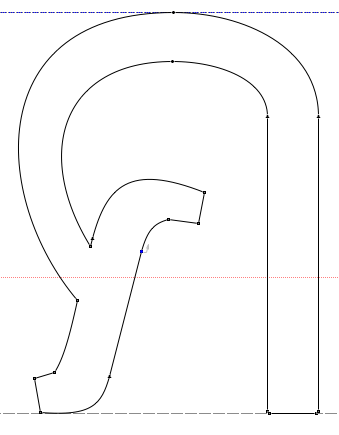
Opentype / Truetype
พอดีช่วงนี้ผมเริ่มอยากลงลึกศึกษาในตัวโปรแกรมมากกว่าศึกษาดีไซน์ครับ
แต่บ้านเรานี่หาอะไรพวกนี้อ่านยากเหลือเกิน ต้องรอผู้รู้  :56:
:07:  แต่จริงครับ ที่ตำราแนวนี้หาอ่านยากครับ อย่าว่าแต่ภาษาบ้านเรา ภาษาปะกิตก็ยังหาอ่านยากอยู่ แม้จะพอหาได้บ้างก็ตาม เป็นศาสตร์ของชนกลุ่มน้อยครับ
:25:  อ้อ...จะบอกว่า อีกข้อนึงคือ ถ้าเราวาดเวคเตอร์ตัวต้นฉบับไว้ได้แบบกิ๊ง กิ๊ง จุดแบบทรูไทป์ก็จะน้อยไปด้วยนะครับ
:48: ลืมบอกไปครับว่า ถ้าจะดูว่าการวาดเส้นแบบกิ๊งๆ จะช่วยให้เวลาคอนเวิร์ดแล้วเส้นจะมีจุดน้อย
:27: ให้ลองเปิด ฟอนต์สารบรรณ ด้วยเอฟแอล แล้วลองดูลายเส้นอ่ะครับ จะเห็นว่าจุดจะน้อยเมื่อเทียบกับตัวอื่นๆ ในชุดเดียวกัน
:33: วาดเส้นให้กิ๊งๆ ช่วยได้จริงๆ นะ
จานโม่ลองคลิกขวาบนเส้นดู มันจะมีให้สลับโหมด Truetype/PS ด้วยนะ
ทีแรกก็คิดว่าเป็ฯเรื่องความถนัด (ตูไม่ชอบการดดัดเส้นแบบอีรัตน์ :3005:)
คือผมถนัดแบบอีรัตน์มากกว่าน่ะครับ รู้สึกว่าโค้งที่ได้มันมีความคมมากกว่า (อธิบายยากวุ้ย :08:)
เข้าใจๆ คือมันเป็นการสะบัดโค้งที่ "จริง" กว่า :12:
(กำลังหัดอยู่ แต่หัดจาก Photoshop นะ)
ขออธิบายด้วยภาพนะครับ
นี่คือการ copy ข้ามจาก FL > AI
จุดที่ได้จะตรงกัน
เทียบกันระหว่าง ก๊อปข้ามจาก FL กับการพิมพ์ใน AI แล้ว create outline
การ gen ฟอนต์ให้เป็นแบบ opentype จะทำให้ได้จุดแบบที่ 1 ถูกใช่มั้ยครับ?  :56:
ข้อมูลเพิ่มเติมแบบเนิร์ดๆ  :01:
กราฟิกมักใช้สิ่งที่เรียกว่า Bezier Curve
(เป็นสมการ Parametric ประเภทหนึ่ง = =")
PostScript จะใช้ Cubic Bezier Curve
ประมาณว่าใช้สมการกำลังสาม
ในขณะที่ TrueType ใช้ Quadratic Bezier Curve
ประมาณว่าใช้สมการกำลังสอง
จุดคู่นึงของ PostScript มีที่บิดสองอัน
จุดคู่นึงของ TrueType มีที่บิดแค่อันเดียว
ดังนั้น จะสร้างรูปอะไรสักอย่างนึง TrueType ต้องใช้จุดมากกว่า!